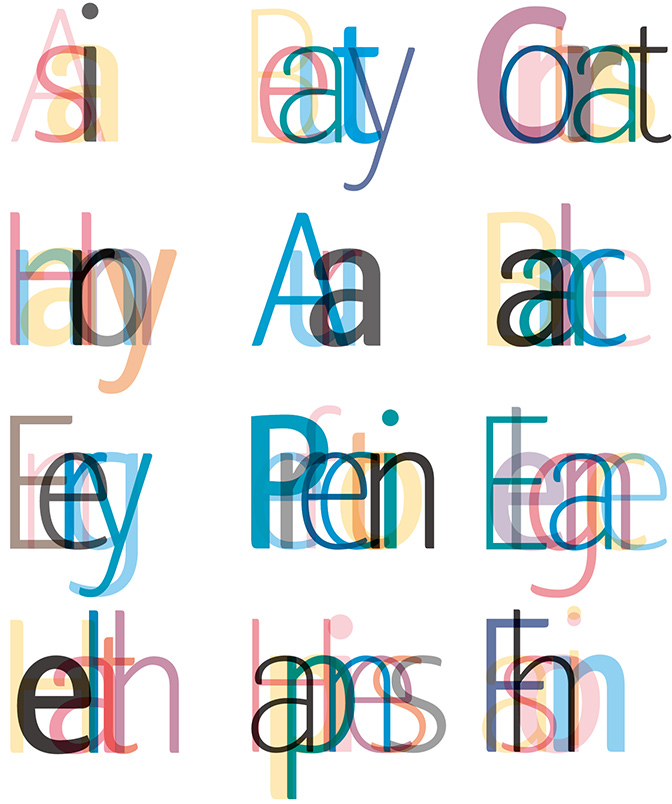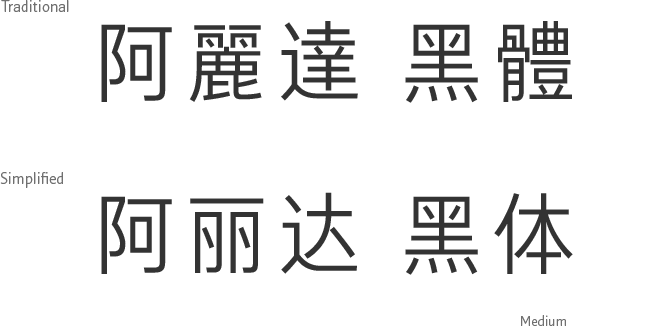
Arita Typeface introduce
Arita(阿麗達)字型蘊含著愛茉莉太平洋的企業識別,以期實現「分享的價值」。
愛茉莉太平洋為與社會創造分享美麗的文化、實踐分享之價值,創造了任何人都能免費使用的企業字型。Arita字型於2016年1月在世界三大設計獎之一的德國iF設計大獎(International Forum Design Awards 2016)榮獲iF傳達設計獎,2015年7月榮獲紅點設計獎。